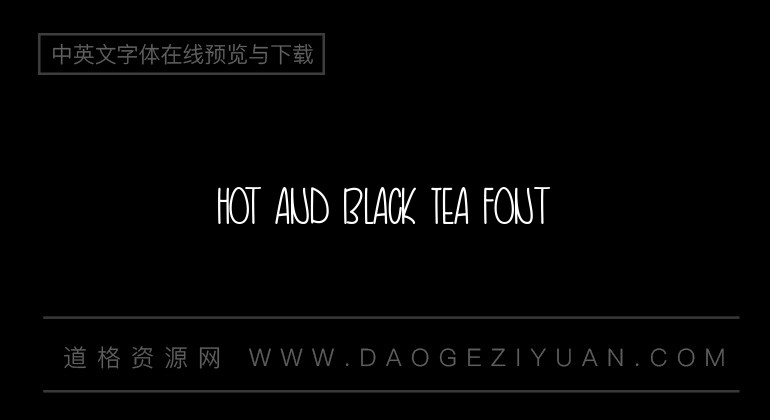
Hot and Black Tea Font
Hot and Black Tea Font 是一款优美的手写字体,具有流畅的线条和纤细的笔画。该字体包括大小写字母、数字和标点符号,适用于各种设计项目,如海报、包装、名片等。该字体的特点是典雅、简约,适合用于展现高品质的设计项目。
Hot and Black Tea Font是一款非常不错的手写艺术字体,具有很好的视觉感,适合于文化类的宣传设计、商业类品牌的广告和产品包装设计以及个性化文字排版等较多场景。